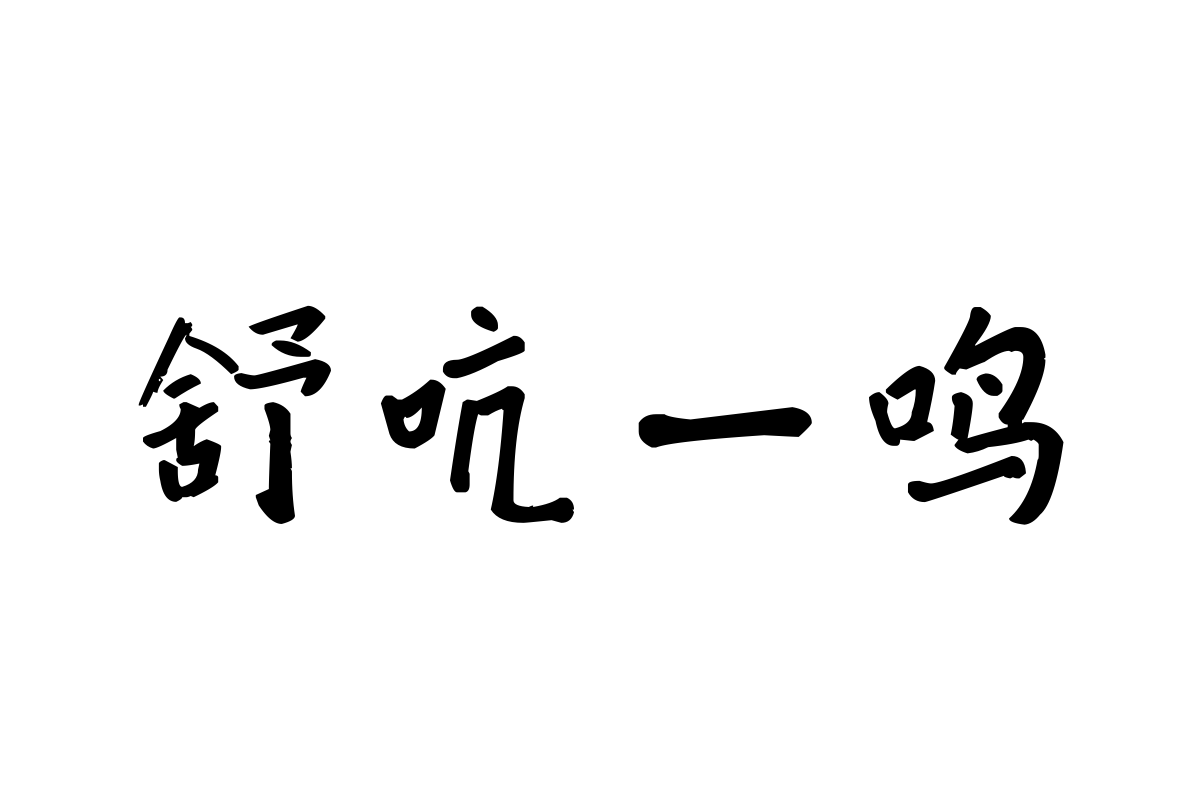
汉标卡拉记号体是一种中文字体,它是由日本设计师田中一郎在1980年代创造的。这种字体的特点是笔画粗细不一,形状独特,具有很高的辨识度和艺术性。它的线条流畅,结构紧凑,给人一种优雅、简洁的感觉。
汉标卡拉记号体适用于各种需要强调文字个性的场景,如广告、设计、印刷等。它的使用可以增加文本的视觉冲击力,提高信息的传达效果。同时,由于其独特的风格,也常常被用于个性化的产品设计中,如笔记本、名片、包装等。